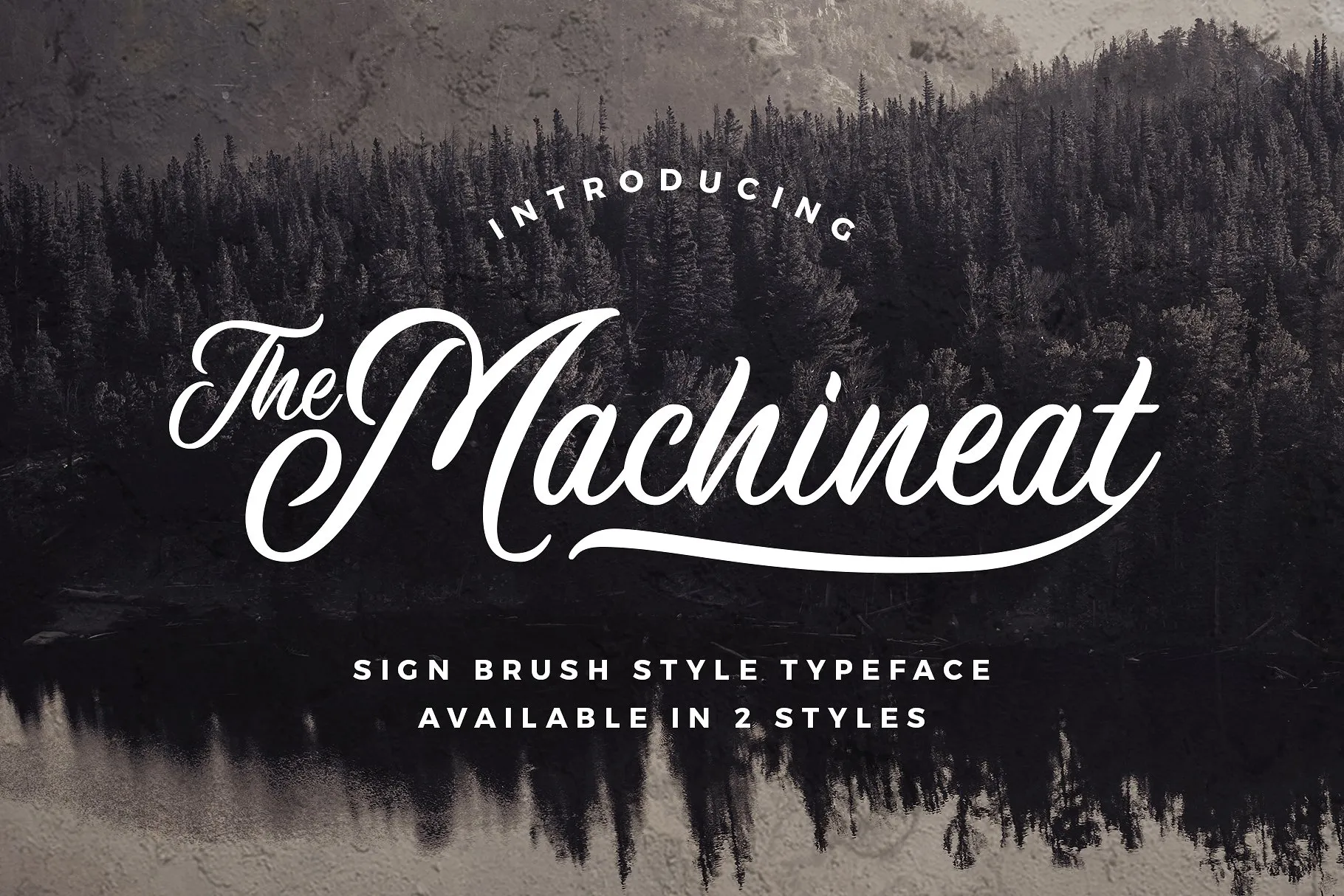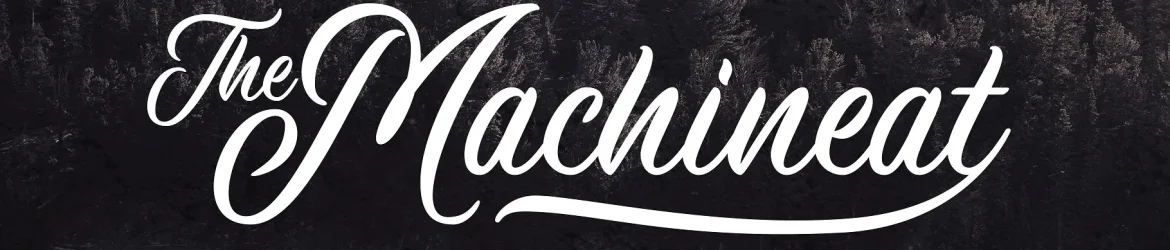
Machineat Script Font – Download Grátis
A Machineat Script Font é uma atraente opção para projetistas que desejam adicionar um toque natural às suas criações digitais. Inspirada nas pinturas tradicionais de sinais manuais, essa tipografia tem um estilo de traço assinado que flui naturalmente e traz uma sensação autêntica à sua produção visual. Ideal para projetos variados como logotipos, folhetos, outdoors, design de roupas, etiquetas, anúncios, designs de produto ou murais, Machineat é um recurso valioso para qualquer designer gráfico que procura estilizar suas obras de forma autêntica e natural. Seu uso permite uma variedade ampla de aplicações, tornando-a uma fonte confiável para projetos em que o design está sempre priorizado. Como parte da família de Wacaksara Co., Machineat se preocupa com cada detalhe para oferecer um produto de alta qualidade e versátil.